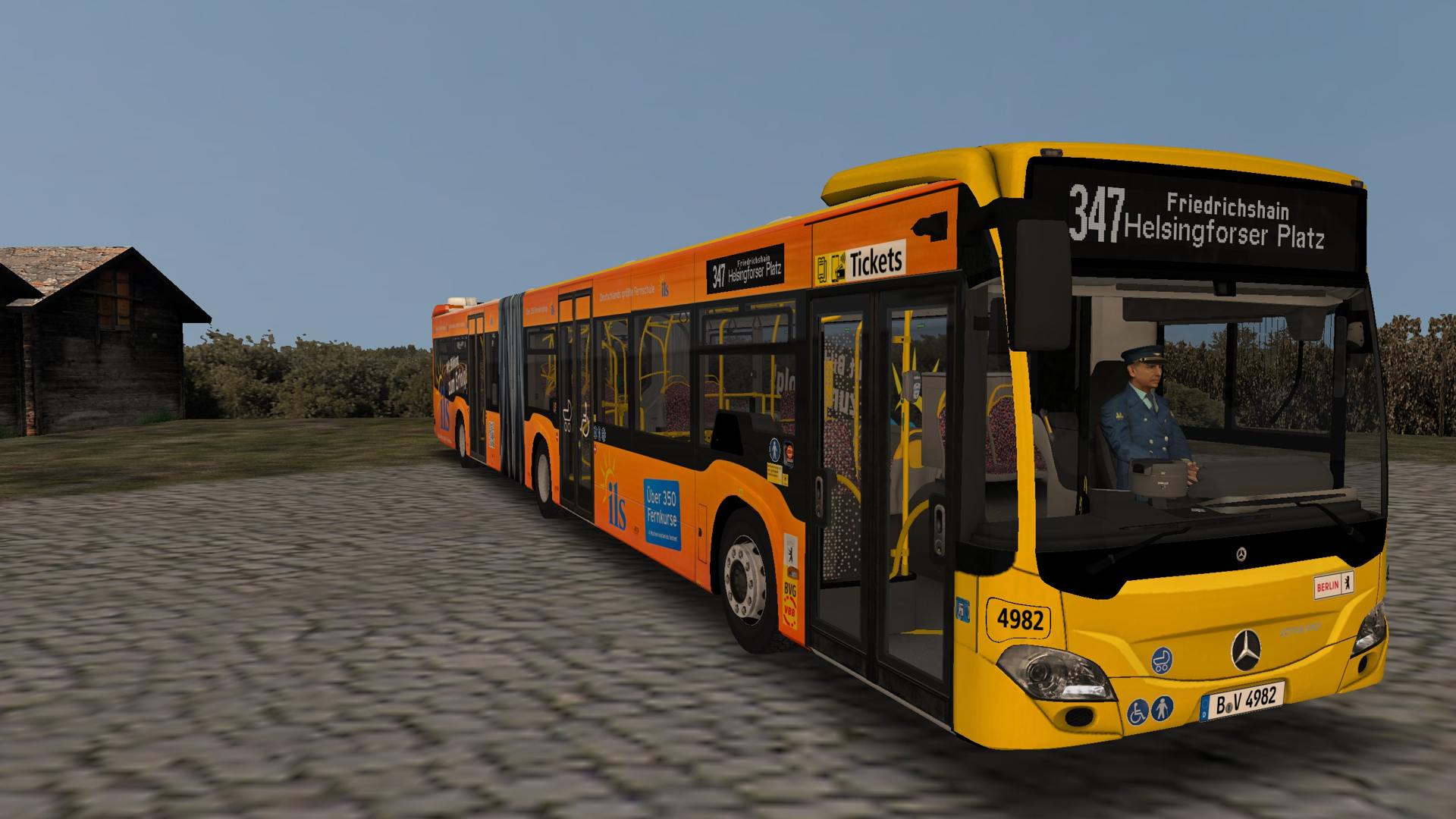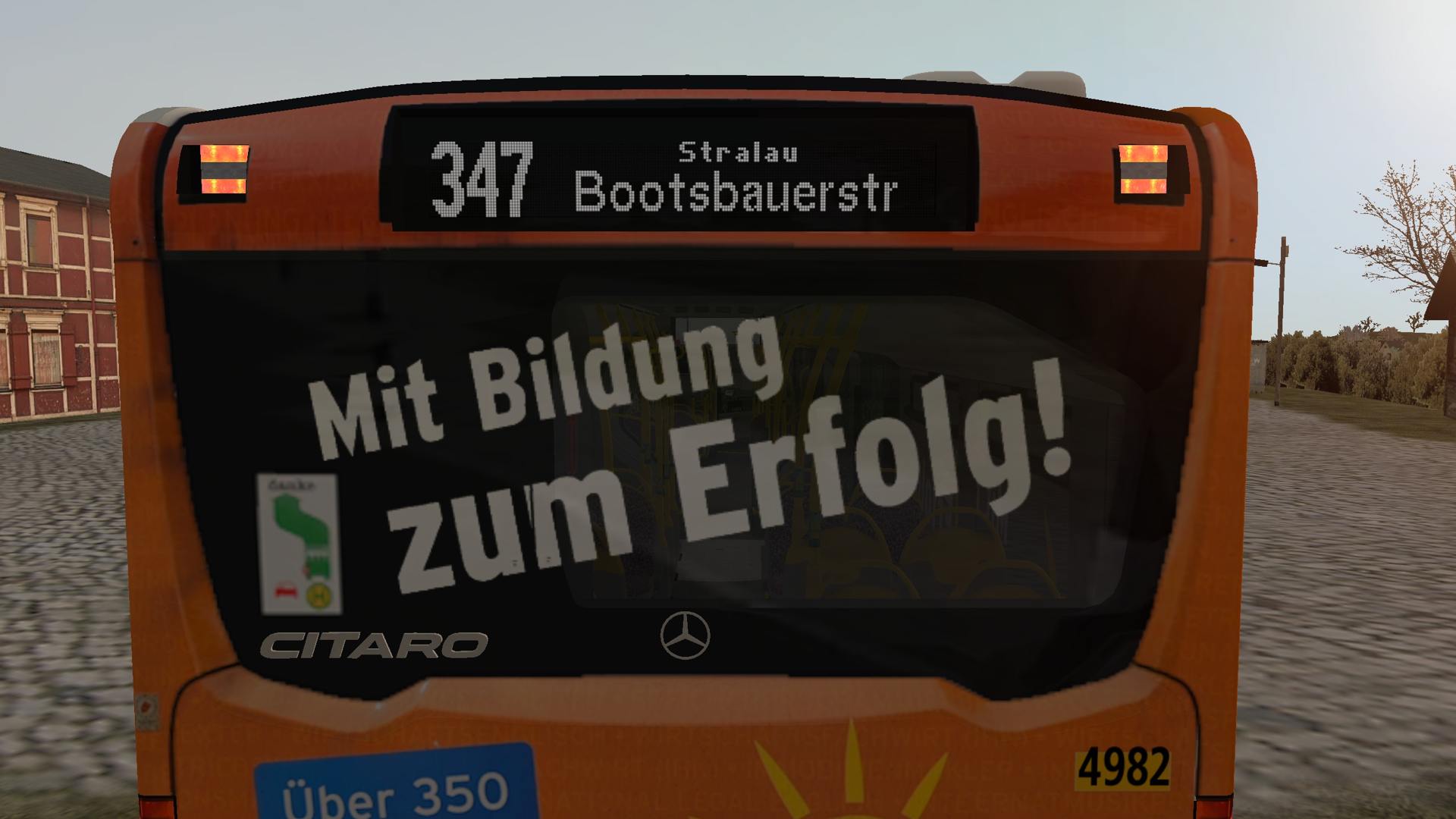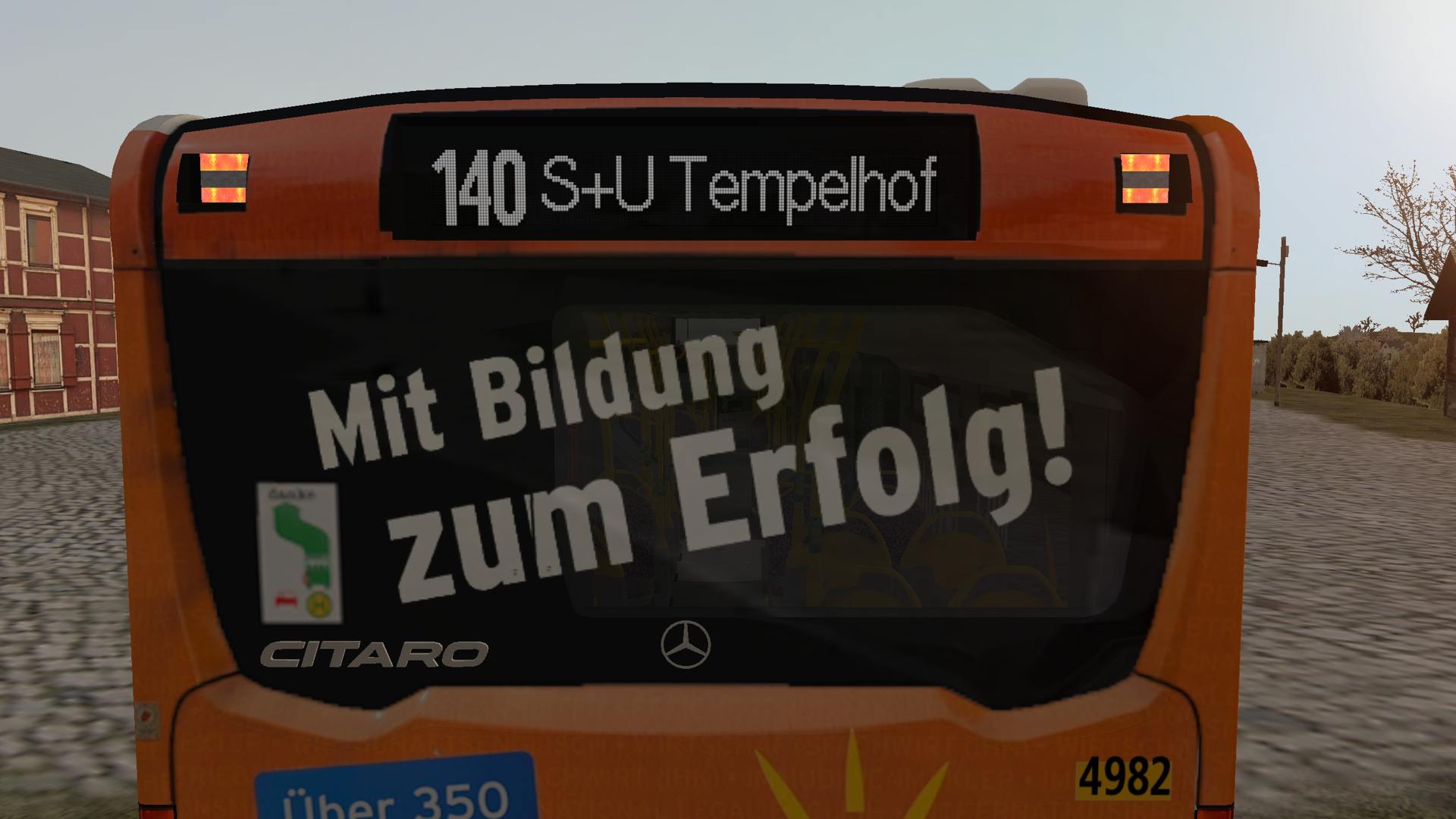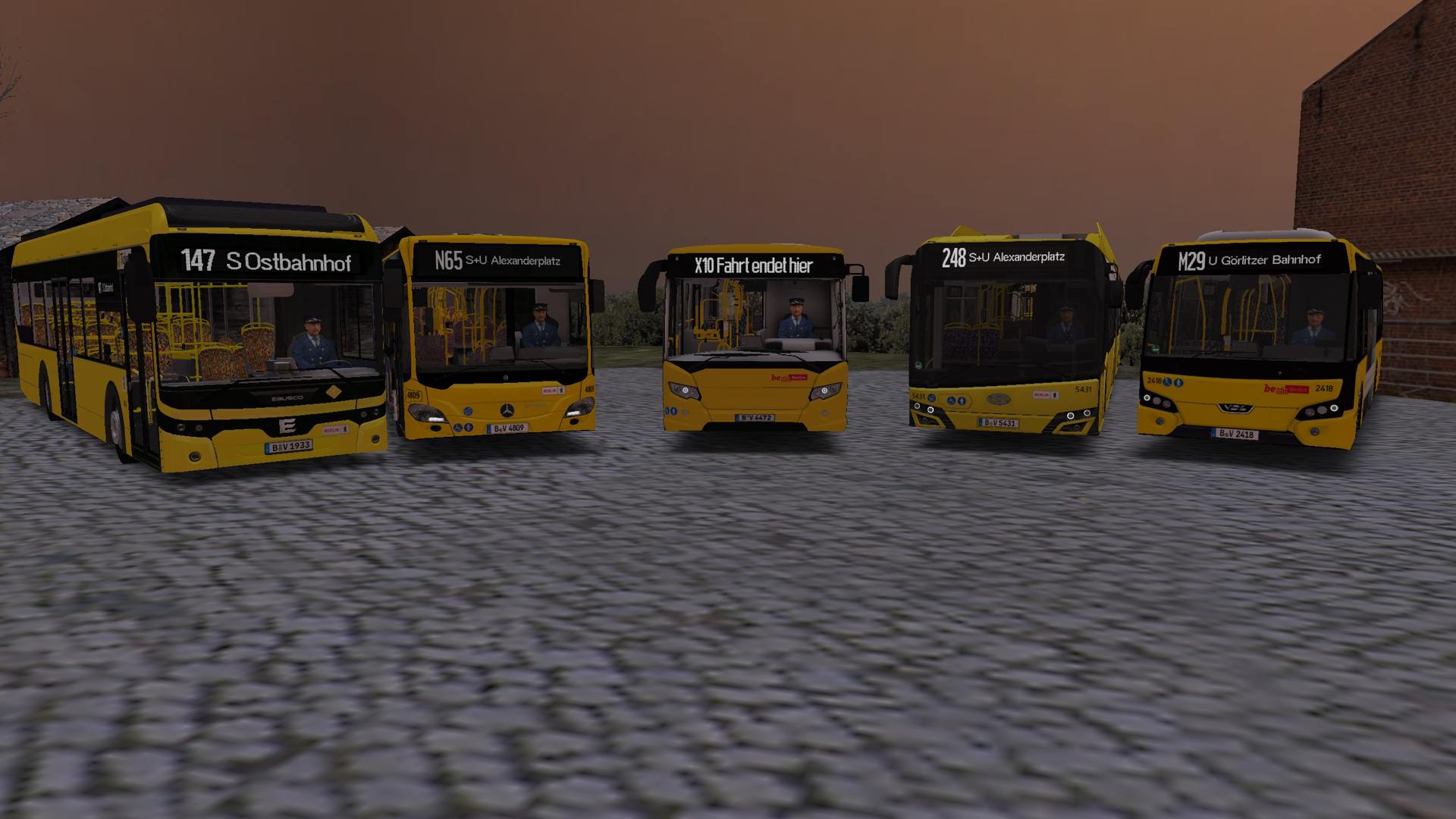
-DE-
In den vergangenen Wochen begann die BVG damit, die Darstellung der Liniennummern auf den Matrixanzeigen zu updaten.
Um euch dieses Update auch im OMSI zur Verfügung zu stellen, habe ich die entsprechende Font für mehrere gängige Fahrzeuge der BVG nachgepixelt.
-EN-
In recent weeks, BVG has begun updating the display of line numbers on matrix displays.
To make this update available to you in OMSI, I have re-pixelated the corresponding font for several common BVG vehicles.
-DE-
- ein und zwei Zeichen Liniennummern werden nun auch mit der neuen Font dargestellt
- Die Font für den Scania GN14 wurde nun auch an die neue Font angepasst (Font ab drei Zeichen wird bei diesem Fahrzeug aufgrund des Scripts auch für ein und zwei Zeichen verwendet)
-EN-
- One and two character line numbers are now also displayed with the new font
- The font for the Scania GN14 has now also been adapted to the new font (due to the script, the font for three characters or more is also used for one and two characters in this vehicle)
Kind of sad, old number fonts looked better